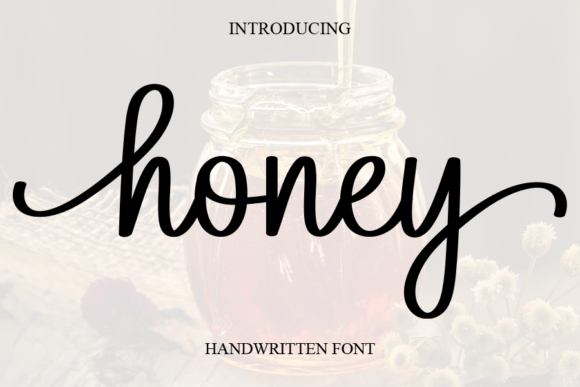
Honey
Honey – A Fonte Cursiva que Transforma Seu Design
Se você está procurando uma tipografia que una elegância e casualidade, a Honey é a escolha ideal. Essa fonte manuscrita, doce e fluida, traz um toque romântico e alegre a qualquer projeto, tornando‑o irresistível para quem valoriza detalhes refinados.
Por que escolher a Honey?
- Versatilidade premium: funciona perfeitamente em branding, logotipos, convites de casamento, cartões de felicitação, lookbooks de moda e campanhas de marketing.
- Leitura agradável: apesar do estilo cursivo, a Honey mantém boa legibilidade, ideal para cabeçalhos impactantes e textos curtos.
- Estilo romântico: linhas suaves e delicadas criam uma atmosfera de carinho e sofisticação, perfeita para projetos que buscam emoções positivas.
- Design casual‑chique: combina o charme de uma escrita à mão com a modernidade de uma tipografia profissional.
Aplicações Ideais da Fonte Honey
- Identidade visual de marcas que desejam transmitir delicadeza e confiança.
- Logotipos de boutiques, floriculturas e negócios de lifestyle.
- Convites e materiais de casamento – desde save‑the‑date até menus.
- Cartões de felicitação, cartões de visita e envelopes personalizados.
- Lookbooks, catálogos de moda e campanhas de redes sociais.
- Peças promocionais como flyers, banners e anúncios digitais.
Honey não é apenas mais uma fonte cursiva; ela é a expressão visual de alegria e romance. Seja para dar vida a um convite de casamento dos sonhos ou para destacar a identidade de uma marca de moda, a Honey entrega sofisticação sem perder o toque casual que encanta o público. Experimente agora e descubra como essa tipografia pode elevar o nível dos seus projetos criativos.